크리에이티브를 위한 24가지 최고의 Blackletter 글꼴
게시 됨: 2022-04-28최고의 블랙레터 글꼴 에 대한 검색은 여기에서 끝납니다. 콘텐츠에 왕실과 고대의 우아함을 부여하는 것이 목표라면 올바른 페이지를 방문하신 것입니다.
고대 텍스트와 스크립트는 블랙레터 글꼴로 채워져 있습니다. 대부분이 성경이었던 유럽에서 처음 몇 권의 인쇄된 책이 모두 블랙레터 글꼴로 인쇄되었다는 사실을 알고 계셨습니까?
블랙레터 콘텐츠로 우아한 표시를 할 수 있도록 최고의 블랙레터 글꼴 목록을 제공합니다.
트렌디한 블랙레터 글꼴
01 . 캠브리지 – 볼드 장식 고딕 글꼴
Envato Elements 플랫폼의 트렌디한 고딕 글꼴 디자인으로 프로젝트에 사용할 수 있는 전문 글꼴입니다. 이것은 개인 홍보용이든 다양한 프로젝트를 위한 모든 편리한 글꼴 옵션이 될 수 있습니다.
연하장, 행사 전단지, 로고 및 기타 모든 관련 디자인에 이 글꼴을 사용할 수 있습니다.
02 . 그랜버그
Granberg는 현대적이고 멋진 블랙레터 서체입니다. 빈티지한 느낌과 동시에 매력적인 현대적인 느낌이 필요한 모든 프로젝트에 매우 편리한 글꼴 옵션이 될 수 있습니다.
로고 디자인, 레스토랑 포스터, 연하장, 브랜드 디자인 및 기타 관련 프로젝트에 사용할 수 있는 글꼴입니다. Envato Elements 마켓플레이스에서 이 글꼴을 얻을 수 있습니다.
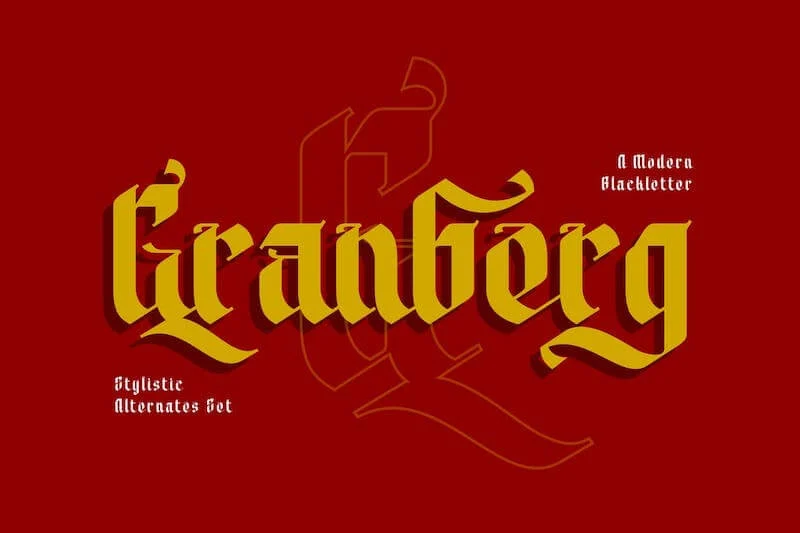
03 . Aceking 글꼴
모든 일반 디자인과 다르게 보이도록 사이트에서 사용할 수 있는 아름다운 빈티지 스타일의 블록체 글꼴입니다. 글꼴은 OTF, TTF, WOFF 등과 같은 여러 형식으로 다운로드할 수 있습니다.
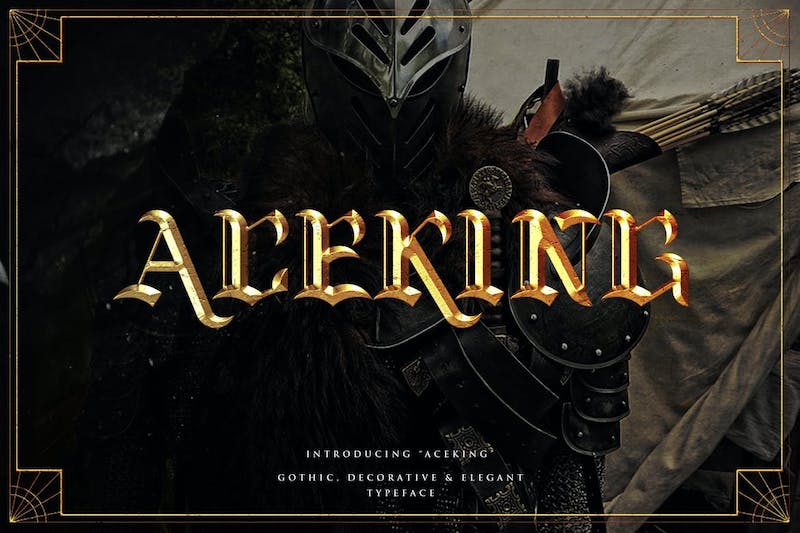
04 . 올드 샬롯
Old Charlotte은 단번에 시선을 사로잡을 수 있는 매우 매력적인 구식 빈티지 고딕 글꼴 디자인입니다. 이 글꼴은 게임 관련 콘텐츠, 로고, 레스토랑 이름, 연하장, 광고판 등에 적합합니다.
05 . 블랙 카메오
이 블랙레터 글꼴은 전 세계 디자이너들이 가장 선호하는 글꼴입니다.
여기서 가장 중요한 부분은 Black Cameo가 고대의 느낌을 줄 뿐만 아니라 로큰롤 터치도 있다는 것입니다.
Black Cameo는 대문자와 소문자를 모두 제공합니다. 또한 525개 이상의 글리프를 얻을 수 있습니다.
모든 알파벳은 초기 및 종료 스타일 세트로 구성되어 글꼴에 매우 표현적인 느낌을 줍니다.
06 . 주류 컬렉션
Bart Wesolek이 디자인한 Liquor Collection은 특히 서구 국가에서 가장 많이 사용되고 유명한 블랙레터 글꼴 중 하나입니다.
이 글꼴의 모양과 느낌은 모두 빈티지입니다. Liquor Collection은 단일 글꼴 스타일이 아니라 블랙레터 글꼴의 묶음입니다.
Liquor Collection은 19개의 독점적인 디스플레이 글꼴과 15개의 사전 제작된 로고 템플릿으로 구성되어 있습니다. 이 글꼴 번들에서 문자 맵도 얻을 수 있습니다.
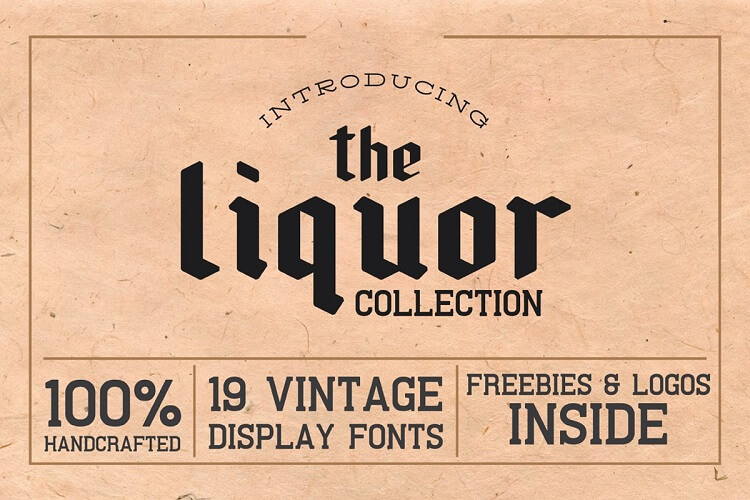
07 . 다크랜드
이름에서 알 수 있듯이 이 글꼴은 아름답고 어둡습니다. Darlands 글꼴은 오래된 고딕 스크립트 글꼴에서 영감을 받았습니다.
글꼴은 콘텐츠에 고급스럽고 빈티지한 영어 텍스트 느낌을 주기에 매우 적합합니다.
세리프 글꼴 유형, 최소 간격 및 큰 문자는 Darklands를 디자이너에게 좋은 선택으로 만듭니다.
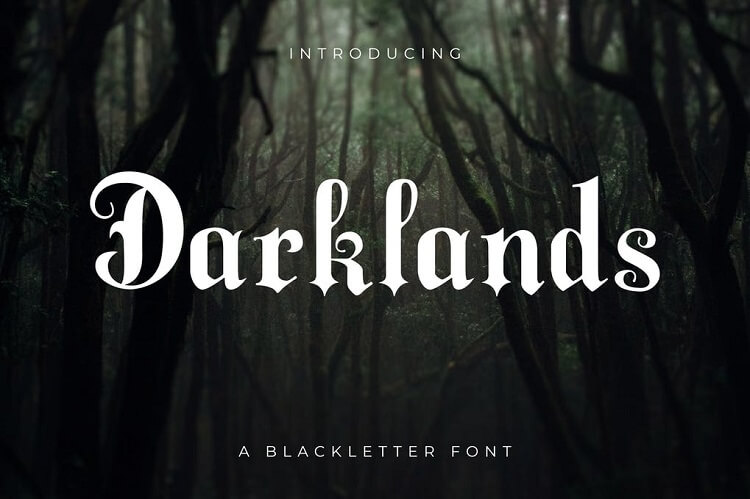
07 . 가명
Incognito는 또 다른 매우 인기 있는 고딕 블랙레터 글꼴입니다. 이 글꼴이 다양한 "로큰롤" 문신과 로고에 사용되는 것을 보았을 것입니다.
관습 및 현대 문신 문화에서 영감을 받은 이 제품은 예술가뿐 아니라 디자이너에게도 훌륭한 옵션입니다.
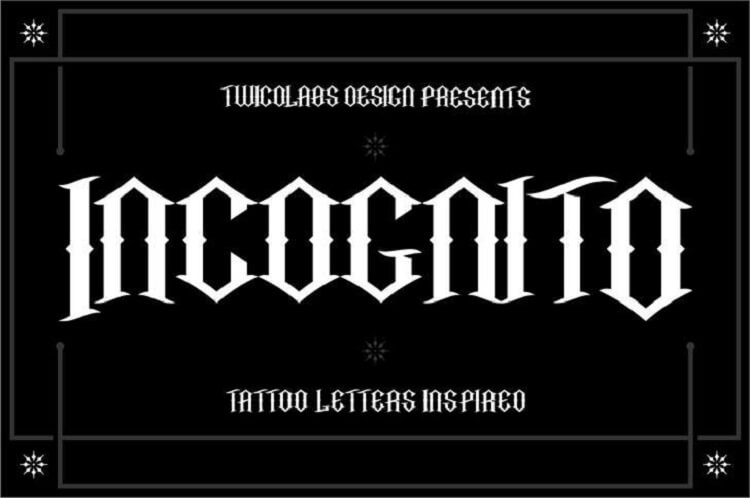
08 . 로체스터
이 목록에서 가장 유명한 글꼴 중 하나인 Rochester 글꼴은 의심할 여지 없이 매우 고급스럽고 현대적입니다.
유명한 예술가이자 글꼴 디자이너인 Roger White가 1993년에 디자인한 이 글꼴은 Roger의 작품을 스캔하여 만들었습니다.
눈에 띄는 섹션을 강조 표시할 뿐만 아니라 부제목을 만드는 좋은 옵션인 Rochester는 모든 종류의 블랙레터 글꼴 애호가에게 훌륭한 옵션입니다.
09 . 동판 텍스트 아카이브
이 고대 글꼴은 20세기 초 미국 표본에서 발견되었으며 그 시작은 현재까지 알려지지 않았습니다.
콘텐츠에 제공하는 디자인과 레이아웃은 모두 고전적이고 중세적입니다. Archive Copperplate Text 글꼴에서 민족적이고 음산하고 소박한 모습을 얻을 수 있습니다.
글꼴은 특히 오래된 중세의 모습을 보존할 수 있도록 추가 문자와 문자로 구성되지 않습니다.
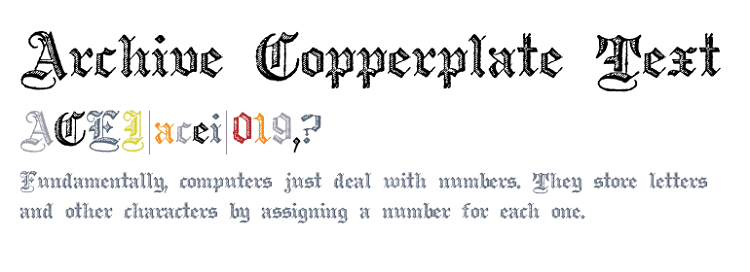
10 . 오지만디아스
이 목록에 있는 아주 어린 글꼴인 Ozymandias는 무료 블랙레터 글꼴입니다. 디자이너에 따르면 글꼴은 선과 다이아몬드 모양을 사용하여 알파벳과 문자를 만듭니다.
문자와 텍스트는 Ozymandias 글꼴에서 놀랍도록 균형 잡히고 단순해 보입니다.
텍스트에서 연속적이고 중세적인 느낌을 주기 위해서는 이 것이 좋은 선택입니다.
11 . 비요르케
블랙레터 디자인으로 특별히 제작된 아름답고 읽기 쉬운 글꼴인 Bjorke는 모든 블랙레터 디자인에 탁월한 선택입니다.
여기서 가장 중요한 부분은 모든 종류의 디자이너에게 제공되는 다용성입니다. 블로그 작가부터 티셔츠 디자이너에 이르기까지 이 글꼴은 많은 것을 제공합니다.
이 글꼴은 또한 일반 스타일과 대체 스타일 모두에서 놀라운 다양성을 제공합니다.
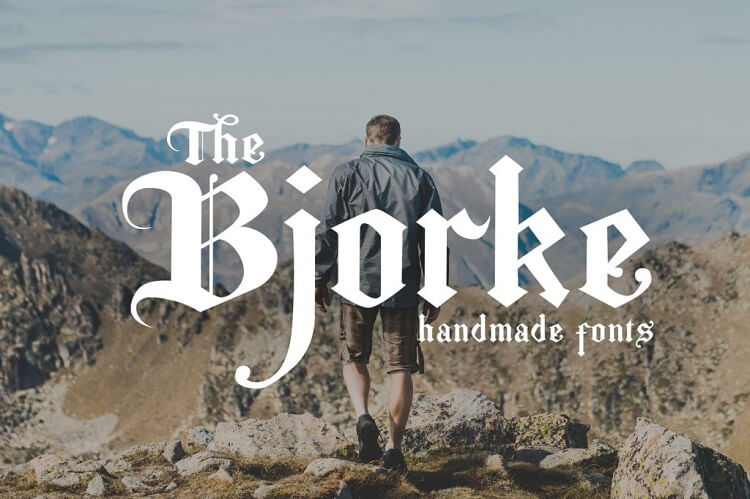
12 . 신성한 연합 글꼴
매우 간단하고 우아한 또 다른 디자인인 Holy Union Font는 모든 종류의 디지털 콘텐츠에 사용할 수 있는 놀라운 블랙레터 글꼴입니다.
이름에서 짐작할 수 있듯이 이 글꼴의 모양과 느낌은 매우 전체론적이고 고대적입니다.
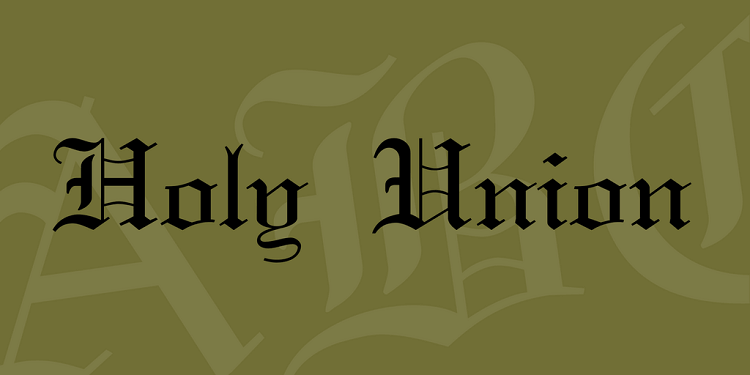
13 . 올 잉그리쉬
글꼴에서 알 수 있듯이 PixelMoshpit에서 영감을 받았습니다. Ole Ingrish를 사용하면 예상치 못한 고딕 양식의 작품을 만들 수 있습니다.
그리고 가장 좋은 점은 글꼴의 기본 무게가 더 적습니다. 이는 제목과 제목을 넘어 글꼴을 사용하는 데 도움이 됩니다.
로고, 셔츠, 연하장 등 모던하고 가벼운 디자인에 사용할 수 있습니다. 다차원 비즈니스의 경우 이것은 훌륭한 옵션입니다.
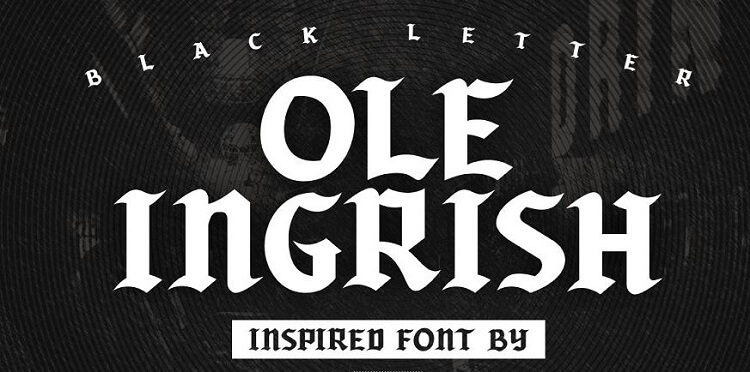
14 . 밀레니엄 블랙레터 서체
Mcraft Studios의 놀라운 제품인 Millenium Blackletter Typeface는 다목적 및 다용도 블랙레터 글꼴입니다.
글꼴은 콘텐츠에 도시적이고 현대적인 느낌을 주는 데 사용할 수 있습니다. 이 블랙레터 글꼴은 둥근 글꼴과 일반 글꼴의 두 가지 글꼴 스타일을 제공합니다.
여기에서 제공되는 고딕 양식의 느낌과 모양은 놀라운 로고, 기사 및 포스터를 만드는 데 사용할 수 있습니다.
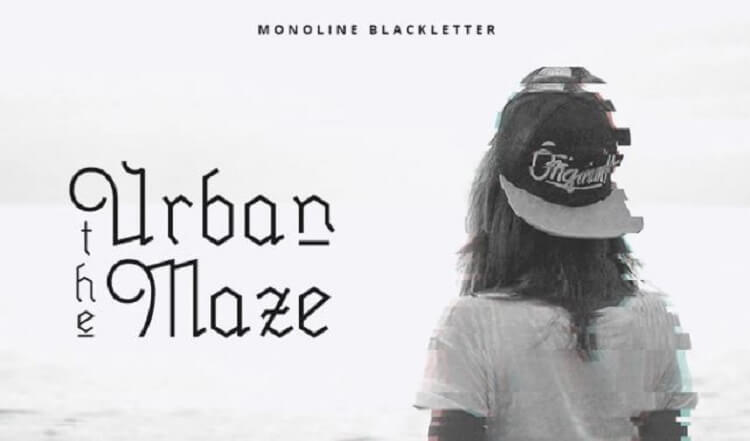
15 . 헬름스발트 포스트
이 글꼴을 간단히 살펴보면 Washington Post의 로고가 생각날 것입니다. 화려한 대문자, 곡선 및 음수 공간이 잘 혼합되어 글꼴이 매우 위협적으로 보입니다.
모든 크기 최적화, 로마자 대문자 및 고대 세리프 스타일이 이 블랙레터 글꼴을 탁월한 선택으로 만듭니다.
여기서 주목해야 할 중요한 점은 두 시대를 똑같이 느낄 수 있는 오래된 알파벳과 새로운 알파벳이 혼합되어 있다는 것입니다.
16 . 암스트롱 서체
Rvq 기술로 디자인된 새로운 글꼴 유형 Amstrong Typeface는 블랙레터 글꼴 디자이너를 위한 훌륭한 옵션입니다.
캐릭터 세트 하나하나가 독특하고 빈티지한 느낌을 줍니다. 현대적인 캐릭터 세트와 빈티지한 캐릭터 세트를 혼합하여 멋진 디자인과 모양을 만들 수도 있습니다.
17 . Jabin Blackletter 글꼴
Jabin Blackletter 글꼴은 당신 안에 그 예술가가 살아있다면 당신이 필요로 하는 전부입니다.
Jabin Blackletter는 다양한 두께와 대비를 제공할 뿐만 아니라 12가지 다양한 글꼴 옵션이 포함된 매우 다양한 글꼴입니다.
현대적인 느낌과 빈티지한 느낌이 조화를 이루고 있으며 무료로 제공되는 이 글꼴은 수익성 있는 거래입니다.